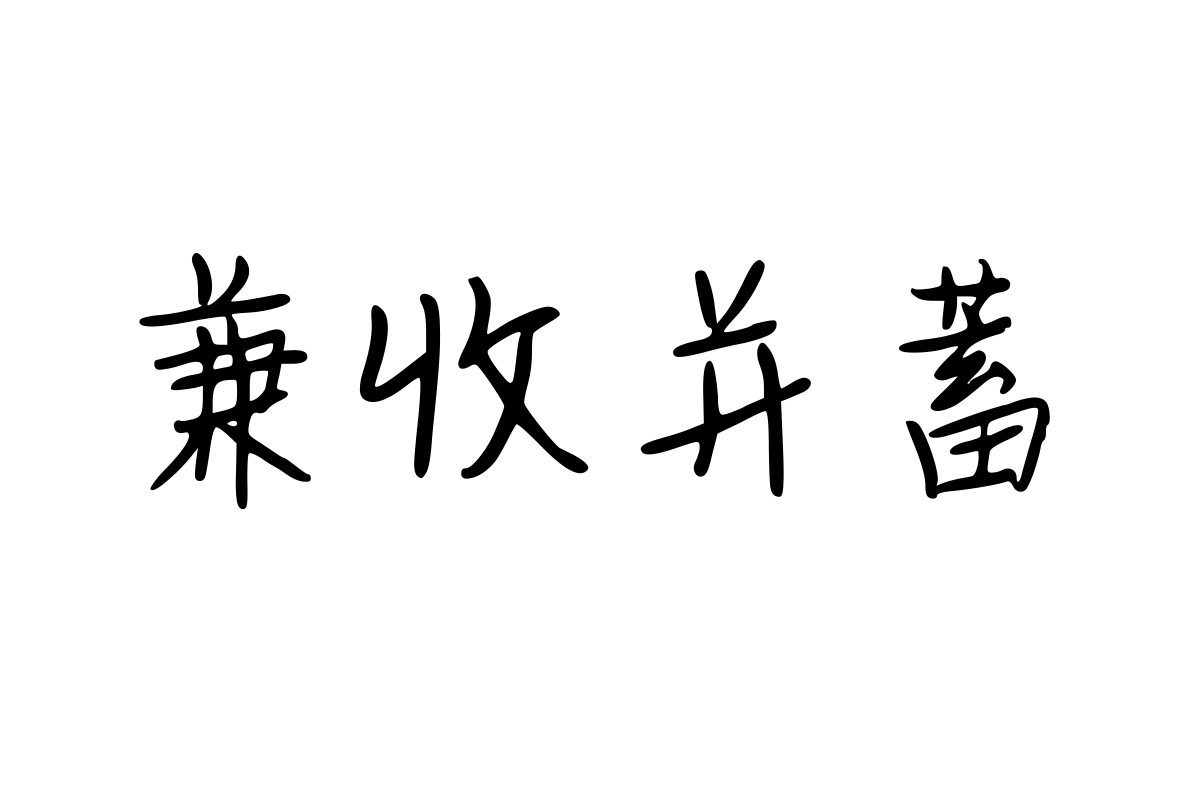
思雨四季如歌是一款具有独特风格的字体,它由著名设计师李浩宇设计。这款字体以其独特的艺术风格和优美的线条而受到广泛赞誉。
思雨四季如歌的笔画流畅自然,字形优美大方。它的字体结构紧凑,每个字都充满了美感和艺术感。这种风格使得思雨四季如歌在视觉上非常吸引人,能够给人们带来一种宁静、舒适的感受。
此外,思雨四季如歌还具有一定的可读性。虽然它的艺术风格独特,但每个字的笔画都经过精心设计,使得整体的可读性得到了保障。这使得思雨四季如歌不仅适合用于装饰,也非常适合用于各种正式场合。
总之,思雨四季如歌是一款非常优秀的字体,它的独特风格和优美的线条使其在众多字体中脱颖而出。无论是用于个人电脑还是手机屏幕,它都能够为你的视觉体验增添一份独特的魅力。